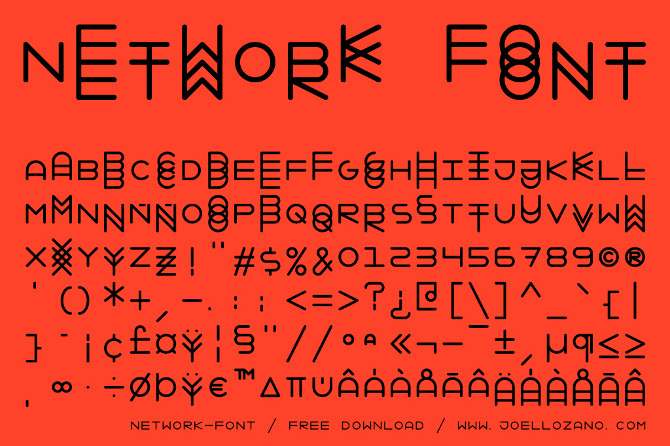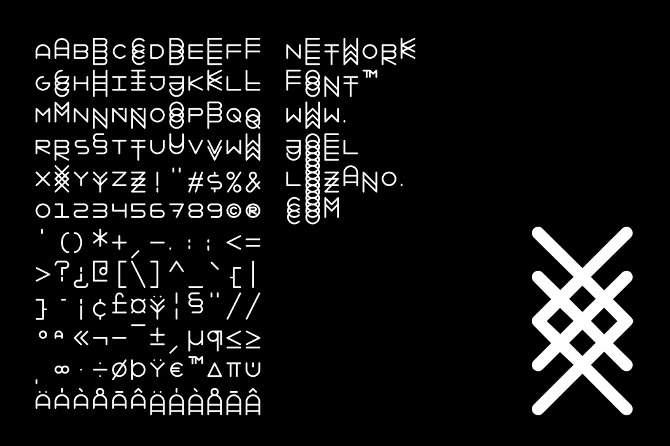
NETWORK FONT
Descripción:
Network Font es una Tipografía Display Monospace, creada bajo el lema de Absolut
Network "Únete. Crea. Comparte", basada en el concepto de unión y que podrá ser
compartida de manera gratuita.